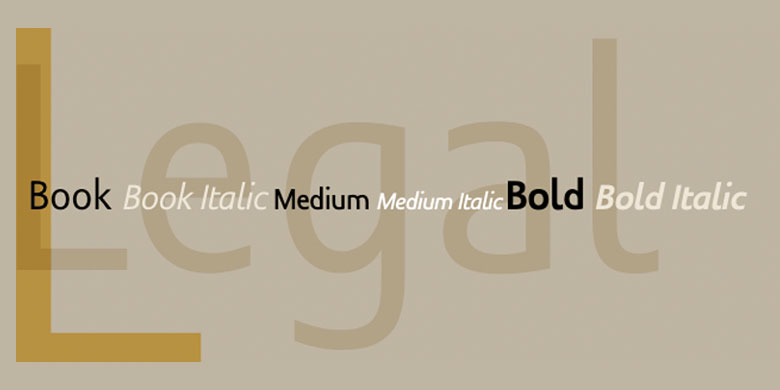
Legal字体家族是从Hellmut G. Bomm于20世纪70年代开始的一个无衬线项目(他的HGB Grotesk)发展而来的。这个精致的工业字体家族非常适合少量的文本、标题、企业标识以及logo设计。字体较小时,该字体与其他许多无衬线字体一样,但字符之间的区别更明显。Legal家族包括Old Figures和真正的Italics。
The Legal typeface family grew out a sans serif project that Hellmut G. Bomm began in the 1970s (his HGB Grotesk). This refined, industrial type family is well suited for short amounts of text, headlines, corporate identity and logo design. In small sizes, the typeface works like many other sans serifs, but with better differentiation between characters. The Legal family includes Old Style Figures and true Italics.